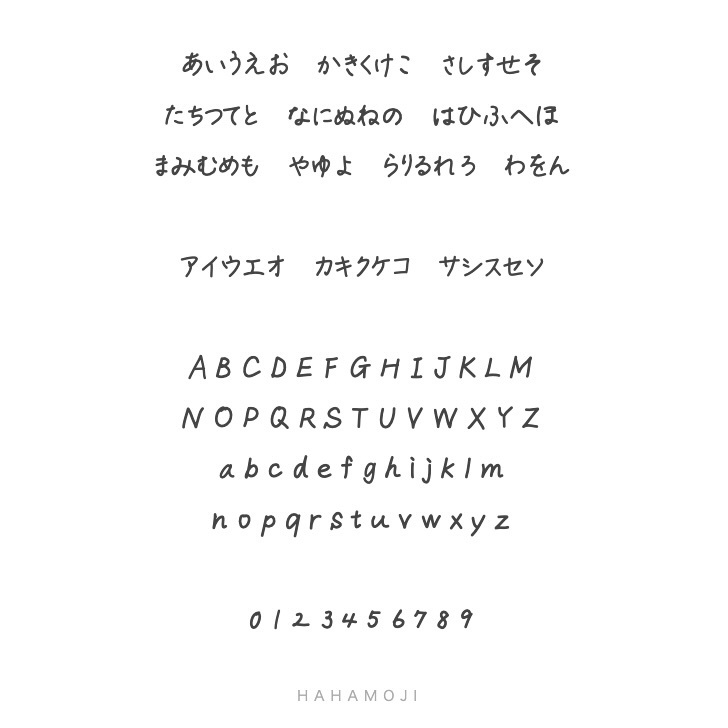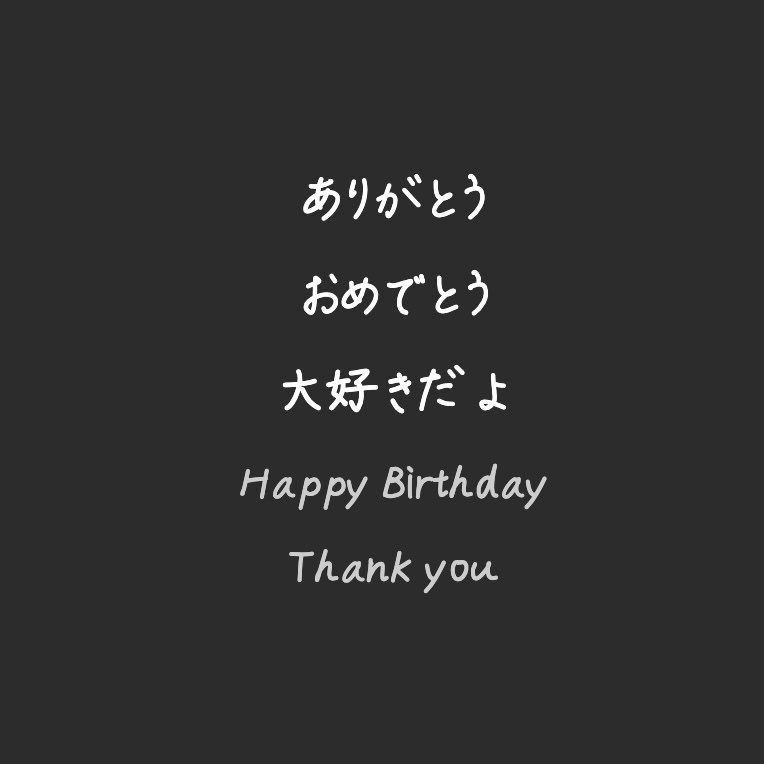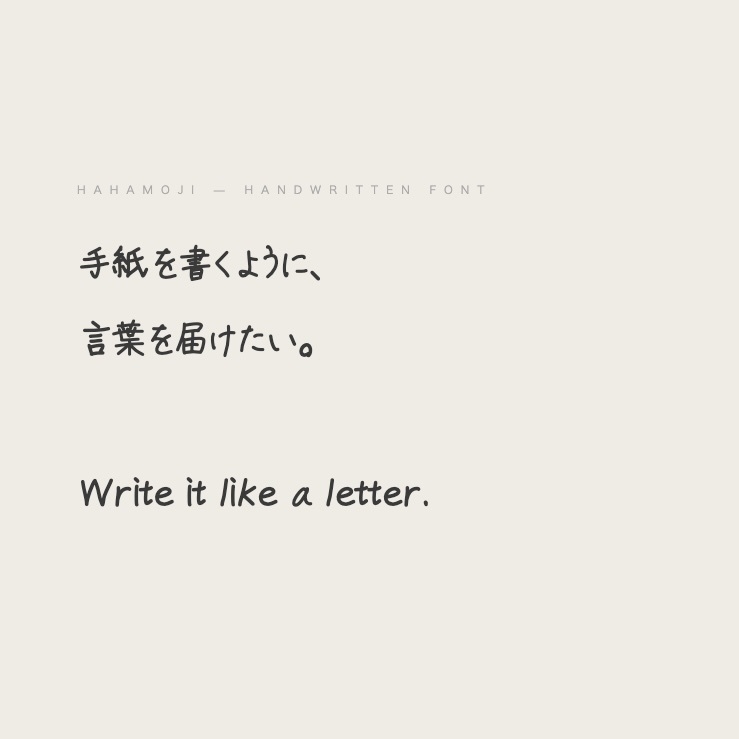
hahamoji|手書きフォント(ひらがな・カタカナ・英数字・漢字対応)
手書きのぬくもりを、デジタルの言葉に。 日常のメモから、大切な人へのメッセージまで。 きれい系の手書きフォント「hahamoji」です。 ───────────────── 【収録文字】 ・ひらがな ・カタカナ ・英数字(大文字・小文字) ・記号 ・漢字(常用漢字を中心に収録) 【ファイル形式】 TTF(TrueType Font) 【動作確認済み】 iOS / Mac / Windows 【使用できるアプリ例】 Vllo・Canva・Word・Keynote・Illustratorなど、 フォントを読み込めるアプリであれば基本的にご使用いただけます。 ───────────────── 【ご注意】 ・個人利用・商用利用どちらもOKです。 ・再配布・販売はご遠慮ください。 ・フォントを使用した作品のクレジット記載は不要です。